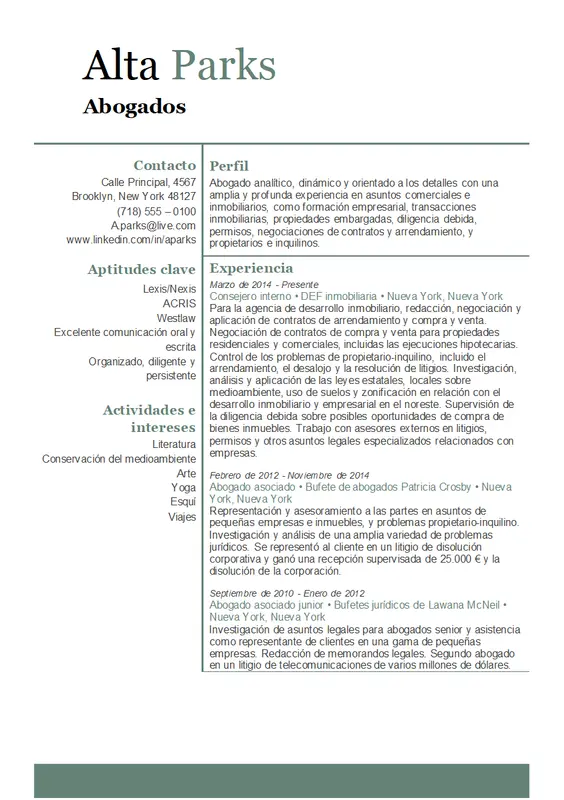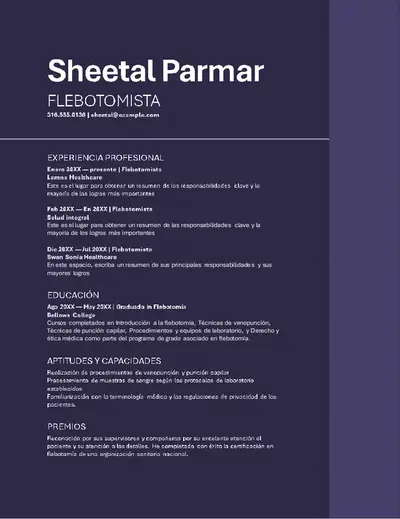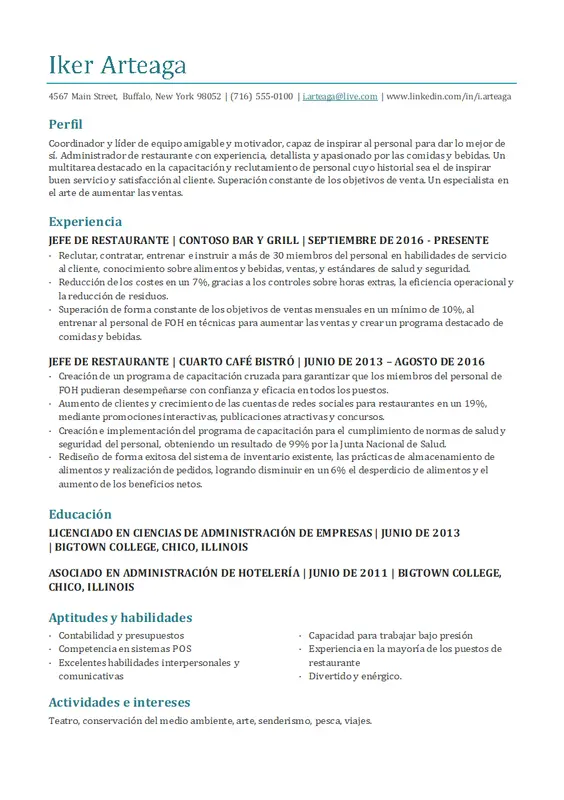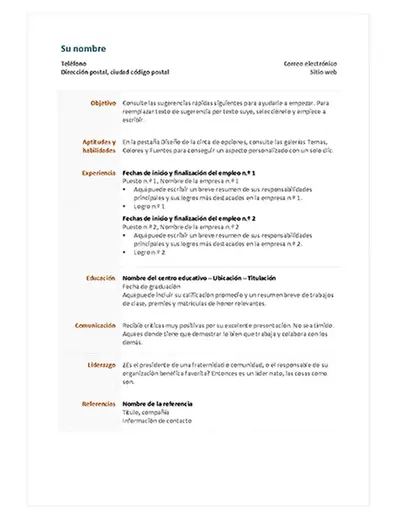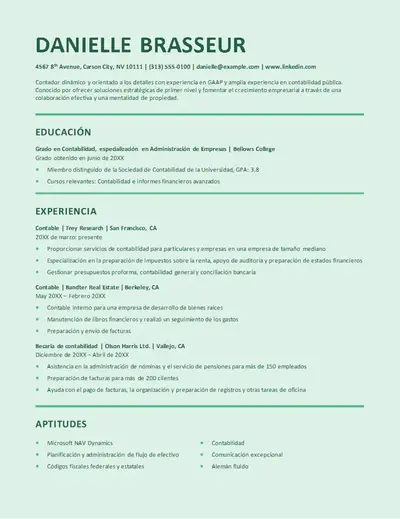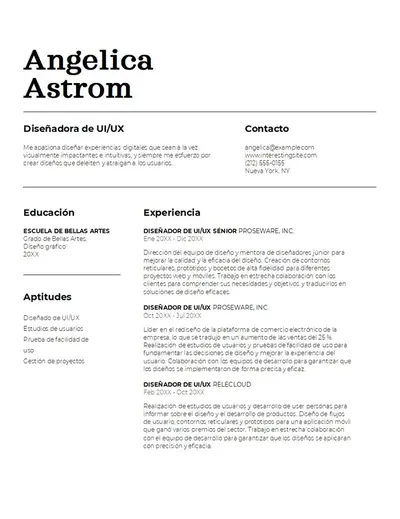
Elegir el tipo de letra correcto para un currículum vítae es una de las formas más eficaces de causar una buena primera impresión. Los tipos de letra pueden comunicar credibilidad y personalidad, apoyar la profesionalidad y perfeccionar un currículum vítae para reflejar la atención al detalle.
Comienza con un currículum bien diseñado con consejos prácticos para elegir estilos y tamaños de fuente adecuados. Aprende a crear una jerarquía de fuentes clara, aplicar formato de forma coherente y crear un currículum vítae refinado en Microsoft Word.
Las seis mejores fuentes de currículum vítae para cualquier solicitud de empleo
El mejor tipo de letra para currículum vítae hace más que aparecer bien en la página. La elección de la fuente define cómo se lee, clasifica y recuerda un currículum vítae. Aquí están las mejores fuentes de aspecto profesional perfectas para redactar un currículum vítae, todas disponibles en Microsoft Word.
1. Fuente Calibri
Calibri, una fuente sans serif moderna, se ha convertido en el estándar de oro corporativo. Fácil de leer, Calibri irradia profesionalismo y autoridad. Con estilos claros y en negrita, este tipo de letra sin serifa se adapta fácilmente a cualquier impresión. Ideal para carreras como derecho, finanzas y atención médica, Calibri se adapta a cualquier rol en el que una apariencia limpia y profesional sea la prioridad.
2. Fuente Garamond
Garamond, un tipo de letra serif clásico, es una opción de confianza en publicaciones profesionales y documentos formales. La fuente es fácil de leer en tamaños más pequeños, lo que le da a un currículum vítae un aspecto autoritario y refinado. Garamond es una opción sólida para roles en la academia, la publicación, el derecho y los puestos ejecutivos donde se valora una presentación tradicional y de alta credibilidad.
3. Fuente Montserrat
Montserrat aporta un aspecto limpio y accesible a un currículum. Montserrat, un tipo de letra ideal para publicidad impresa y letreros urbanos, es ideal para currículos en campos creativos, bienestar y bienes raíces. Esta fuente sin serifa tiene una sensación audaz a la vez que es extremadamente clara y escaneable.
4. Fuente Candara
Candara es una opción sutilmente elegante que se ve pulida sin ser demasiado formal. Fácil de leer con un estilo distintivo, este tipo de letra se adapta a los currículos que tienen menos texto pesado, como un formato de currículum vítae combinado y funciona especialmente bien para pasantías, software y roles de TI.
5. Fuente Cambria
Cambria es un tipo de letra serif tradicional y equilibrado que transmite fiabilidad y profesionalidad. Diseñado para fácil de leer en pantalla (opens in a new tab) en tamaños de texto pequeños, Cambria es una opción sofisticada que se adapta a cualquier currículum. Esta fuente serif funciona bien para roles de administración, recursos humanos y liderazgo, y es una buena opción para currículums de ingeniería y arquitectura, ya que el diseño admite símbolos de matemáticas y ciencias.
6. Fuente Aptos
Aptos es la fuente predeterminada en Microsoft Word y Microsoft 365 que equilibra el estilo contemporáneo con una gran legibilidad para crear un currículum vítae claro y escaneable. Diseñado para facilitar la lectura en pantallas modernas con un tono más cálido y neutro, Aptos (opens in a new tab) es una fuente sin serifa flexible que se adapta a través de títulos y texto de cuerpo. Este tipo de letra contemporáneo es adecuado para aplicaciones tecnológicas, sanitarias y de gestión.
7. Fuente Arial
Arial es un tipo de letra sin serifa, limpio y sencillo, que proporciona a su currículum un aspecto profesional y fácil de digitalizar. Su flexibilidad lo convierte en una opción práctica para currículums en todos los puestos de trabajo y etapas profesionales, ya sea compartido digitalmente o en forma impresa. Este tipo de letra ordenado y coherente es especialmente compatible con aplicaciones corporativas, orientadas al cliente y centradas en el negocio.
Cómo elegir una fuente de currículum vítae profesional
Con una lista corta de fuentes adecuadas seleccionadas, el siguiente paso es encontrar la coincidencia adecuada para el aplicación de trabajo. Elegir la fuente correcta en función del puesto de trabajo y el nivel de antigüedad implica comprender los matices culturales y profesionales de cada sector laboral, así como la impresión que debe causar en los posibles empleadores. Estas son algunas instrucciones para ayudarle a encontrar la mejor fuente.
Considera el puesto y el nivel del puesto
Los diferentes roles de trabajo y los niveles de antigüedad pueden influir en la creatividad o formalidad del diseño y la fuente de un currículum vítae. Tenga en cuenta el nivel de antigüedad del rol, nivel de entrada, nivel medio o senior, ya que esto determina cuánta libertad creativa puede tomar la elección de la fuente.
Por ejemplo: Calibri puede dar a un currículum un aspecto limpio y profesional para un puesto directivo, mientras que Montserrat puede añadir un aspecto más contemporáneo para los puestos en campos creativos.
- ¿Cómo editar la fuente y el tamaño de fuente de un currículum vítae en Word?
Abre un currículum vítae en Word, selecciona el texto que quieres actualizar y usa la lista desplegable de fuentes de la pestaña de inicio para elegir una nueva fuente. Ajusta el tamaño del texto utilizando el campo de tamaño de fuente situado junto a él. Para actualizar todos los títulos o el texto del cuerpo a la vez, haga clic con el botón derecho en el estilo relevante en la galería de estilos y seleccione modificar. El cambio se aplica automáticamente en todo el documento. Para ver más formas de editar y dar formato a documentos en Word, explore editor de documentos.